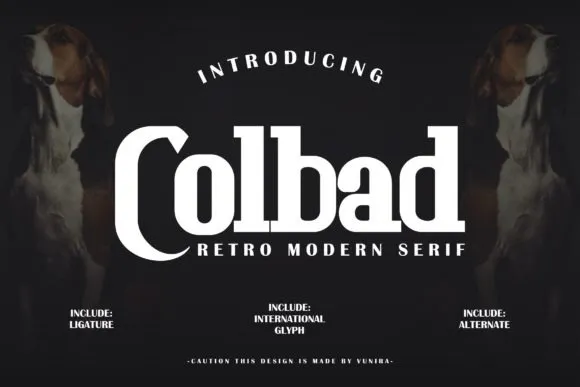
Essa é uma fonte de tipo sólido sérvio (slab serif) chamada Colbad Font, criada pelo designer Vunira. Ela oferece um contraste interessante entre a curvatura e a robustez dos caracteres, tornando-a versátil para diferentes usos. Com sua arrumação clara e linda das letras, esta fonte vai brilhar em projetos tanto formais quanto informais. Colbad é ideal para quem busca uma estética vintage na moda moderna. Ela tem um tom alegre e nostálgico que faz com que seus caracteres sejam divertidos de usar sem perder sua elegância, tornando-a perfeita para designers buscando uma harmonia entre o clássico e o contemporâneo em seus trabalhos. Colbad é perfeitamente adequada para criações que exigem uma transição suave entre a formalidade e a informalidade, tornando-o um recurso valioso para qualquer designer ou criador de conteúdo que busque adicionar personalidade ao seu trabalho visual.